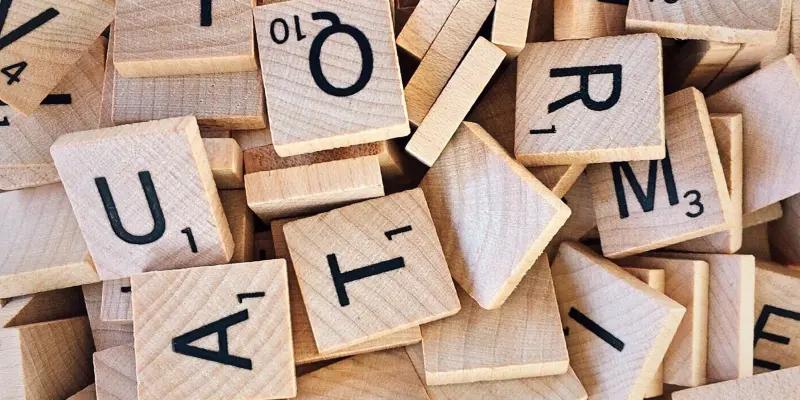
En el entorno del marketing, cada decisión cuenta. Desde los colores y las imágenes hasta los lemas y los nombres de marca, existen muchos trucos de psicología del marketing que pueden influir en la decisión de un cliente potencial de comprar en su empresa. Las fuentes juegan un papel sorprendentemente importante en esta elección. Las fuentes que usted elija pueden comunicar diferentes mensajes al espectador y dictar cómo perciben su marca o producto. Por ejemplo, las fuentes de publicidad en negrita son más llamativas y exigentes, lo que sugiere una personalidad más fuerte que las fuentes neutrales.
Serif vs Sans Serif: ¿Cuál es la Diferencia?
Antes de explorar las mejores fuentes para publicidad, debemos comprender la diferencia entre los tipos de letra, específicamente serif y sans serif. Estas categorías se mencionan a menudo al hablar de fuentes, y usted debe comprender sus diferencias para poder elegir las fuentes de publicidad adecuadas.
La diferencia entre serif y sans serif es sencilla. Una fuente serif tiene un trazo decorativo llamado, sorprendentemente, serif en su diseño. Un serif, a veces llamado las 'patas' de una letra, es un pequeño toque al final del tallo de una letra. Por lo tanto, una fuente serif es un estilo de fuente que tiene serifs en los tallos de sus letras. Por otro lado, una fuente sans serif no lo tiene, después de todo, sans significa in'.
Hemos usado la fuente serif Times New Roman y la fuente sans serif Helvetica en nuestro ejemplo aquí. Como puede ver, las letras de la fuente Times New Roman terminan con serifs ornamentales, mientras que Helvetica tiene extremos nítidos y limpios.
Ambos estilos de tipografía son siempre populares; sin embargo, comunican mensajes diferentes a su público. Los diseñadores utilizan comúnmente fuentes serif en periódicos y libros, y emanan valores tradicionales y confiables. Se remontan a la década de 1700, cuando las letras y las placas se tallaban en piedra, de ahí que todavía veamos estas fuentes como clásicas y refinadas. Empresas que utilizan fuentes serif incluyen Vogue, Apple y Giorgia Armani.
Por otro lado, las fuentes sans serif sugieren una marca moderna y más accesible. Abandonando el camino tradicional de sus contrapartes, las fuentes sans serif abrazan el minimalismo y la frescura. Además, las líneas limpias y sencillas de las fuentes sans serif las hacen más fáciles de leer, razón por la cual los diseñadores web las prefieren para anuncios online. Empresas que utilizan fuentes sans serif incluyen Facebook, Google y Spotify.
Las Mejores Fuentes para Publicidad
Helvetica
Helvetica no es en vano coronada como la fuente más popular en publicidad. Esta fuente sans serif es nítida, limpia y neutral, y se utilizó por primera vez en anuncios que datan de la década de 1950. Una altura de x alta (la distancia entre la base y la parte superior de las letras minúsculas en un tipo de letra) y líneas en negrita hacen que Helvetica sea súper fácil de leer incluso a distancia. Debido a su simplicidad y versatilidad, puede usar Helvetica con casi cualquier campaña publicitaria.
Bodoni Moda
Bodoni Moda fue creada para la era digital, una versión profesional y moderna de un tipo de letra serif clásico. Inspirada en la fuente Bodoni tradicional, esta versión proporciona líneas elegantes y contrastantes para aportar una elegancia que el tipo de letra original carece. El famoso diseñador Massimo Vignelli, conocido por usar solo unos pocos tipos de letra durante su carrera, consideraba al clásico Bodoni original uno de sus principales tipos de letra. Sin embargo, tenemos la corazonada de que también añadiría este toque único a su lista. Con una gama de características y tamaños disponibles en esta familia de fuentes contemporáneas, la adaptabilidad de Bodoni Moda la hace ideal para una gama de estilos publicitarios, particularmente para empresas y productos elegantes y modernos.
Copperplate
En una variedad de productos sorprendentes, incluyendo tableros de Monopoly, portadas de álbumes y botellas de vino, Copperplate ha sido un estilo de fuente popular desde su lanzamiento en 190Logra una mezcla de tipos de letra serif y sans serif, con serifs pequeños y elegantes que resaltan la solidez de las letras, creando un estilo que es fácil de leer y extremadamente notable. Aunque se ha vuelto un poco genérico desde su introducción, Copperplate sigue siendo un tipo de letra favorito entre los anunciantes y diseñadores debido a su elegante neutralidad.
Trajan
Inspirada en el diseño del alfabeto romano (los diseñadores incluso tomaron su nombre de un emperador romano y los tributos que le dejaron), Trajan es una fuente serif introducida en 1989 para Adobe. La fuente es bastante imperial en su diseño, emulando las letras que los romanos cincelaban en piedra, y tiene una presencia elegante pero inquebrantable. Aunque quizás no tan popular como otras fuentes publicitarias en nuestra lista, Trajan ciertamente tiene una posición popular en la tipografía, con marcas corporativas y de ropa que incluyen la fuente en sus proyectos. Trajan es una fuente perfecta para cualquier formato y se utiliza mejor para representar una marca tradicional y confiable con valores y creencias sólidos.
Avenir
Avenir es una fuente sans serif clásica moderna diseñada por Adrain Frutiger, uno de los tipógrafos más icónicos del siglo XX. Su nombre es francés para 'futuro', rindiendo homenaje a la fuente Futura de la que este tipo de letra toma su inspiración, mientras le da un toque único y contemporáneo. Frutiger pretendía que Avenir se usara en un formato en negrita para texto blanco sobre negro, ya que seguiría pareciendo igual que el negro sobre blanco. Sin embargo, Avenir es una de las fuentes más descargadas de Internet y le dará a cualquier diseño una nueva forma y perspectiva, ya sea que opte por usar los colores preferidos del diseñador o no.
- ¿Cómo puedo elegir la fuente adecuada para mi campaña? Considere su público objetivo, el mensaje que desea transmitir y el estilo general de su marca.
Recuerda que la elección de la fuente adecuada es crucial para el éxito de tu campaña de marketing. Experimenta, prueba diferentes opciones y elige la que mejor represente tu marca y conecte con tu público objetivo.